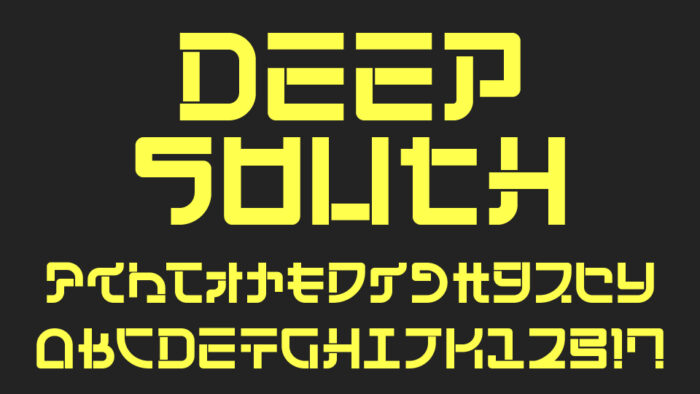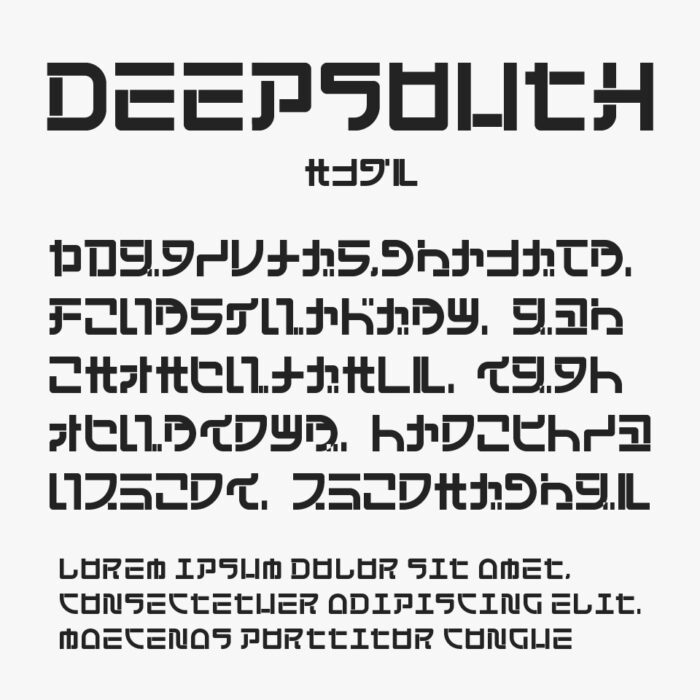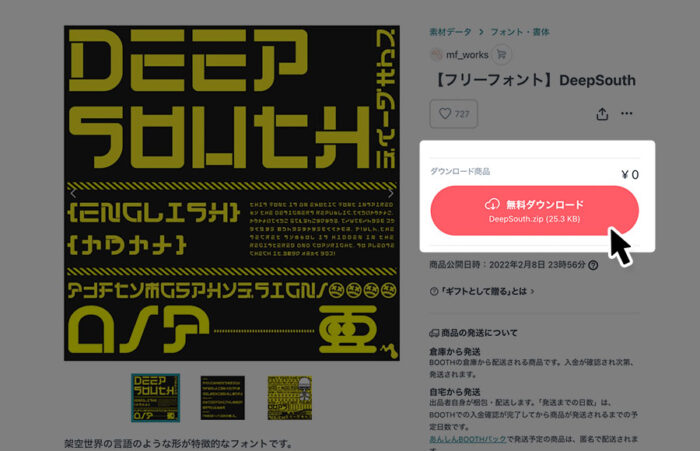
DeepSouth
DeepSouthフォントは、近未来感と機械的を融合させたSFテイストの架空世界の言語のようなデザインフォントです。
直線的で幾何学的なフォルムが、ロボットやサイバー世界を思わせる独特の空気を漂わせます。架空言語のようなデザインですが、読めなさそうだけど読めてしまう文字が面白いですね。
文字の中にも細かなで絶妙な装飾が施されているのもかっこ良い仕上げとなっています。
収録文字は、ひらがな・カタカナ・アルファベット・数字・記号が収録されています。